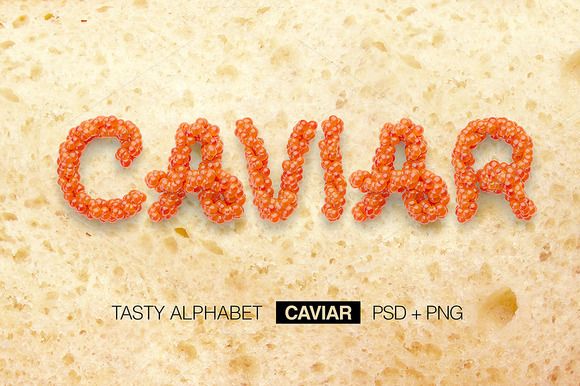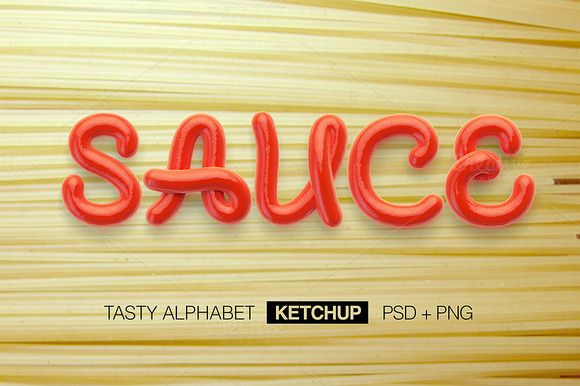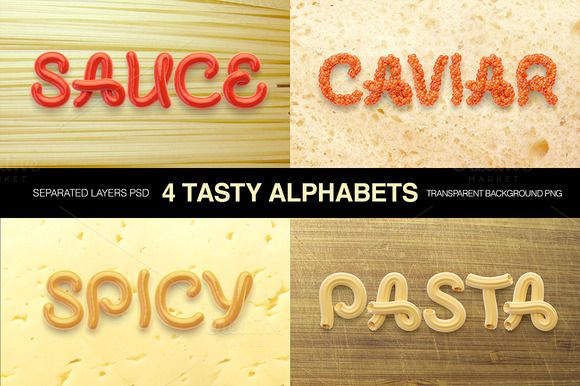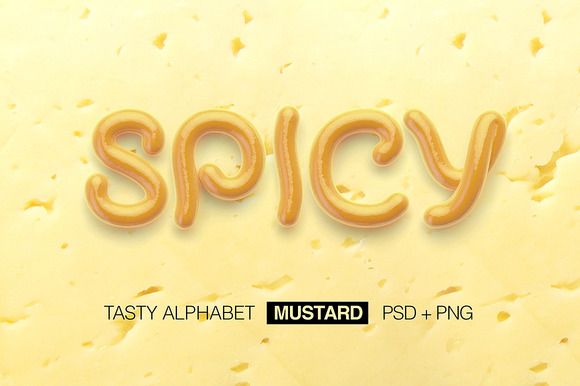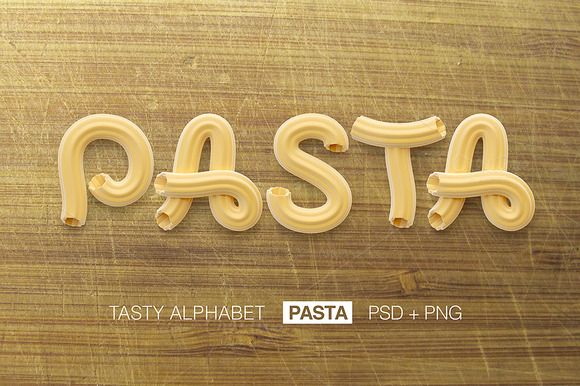
Tasty letters font - декоративный алфавит из пищи
Комплект с 4-мя декоративными алфавитами из разных вещей пищи (макароны, кетчуп, горчица, красная икра). Каждая буква файл имеет разрешение 1000x1000 пикселей.